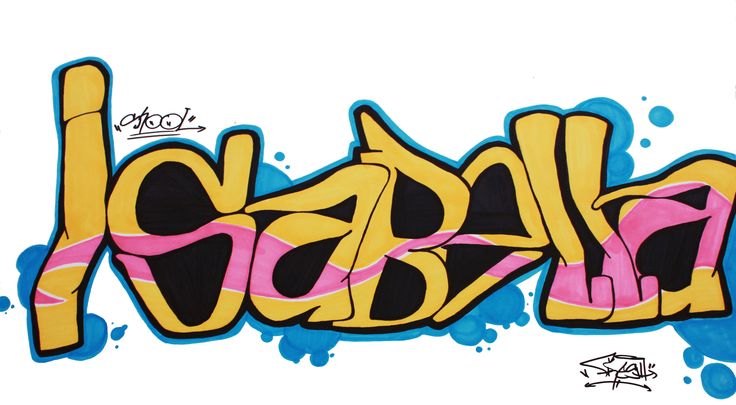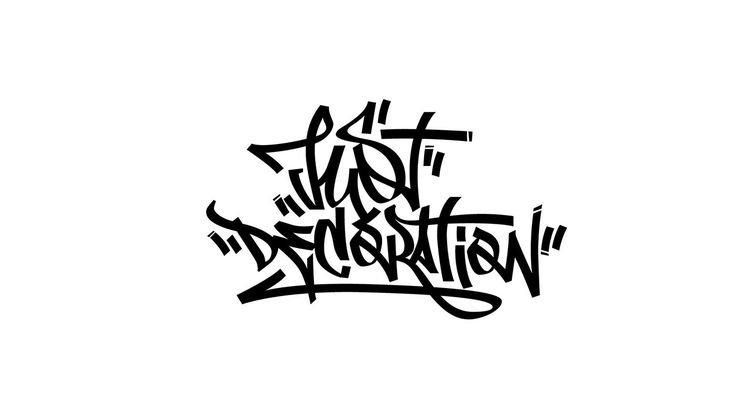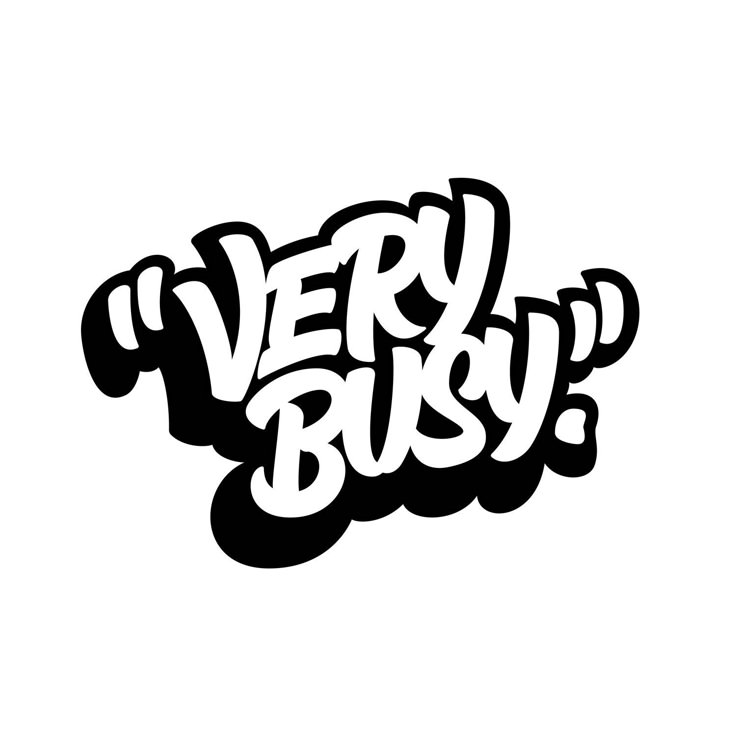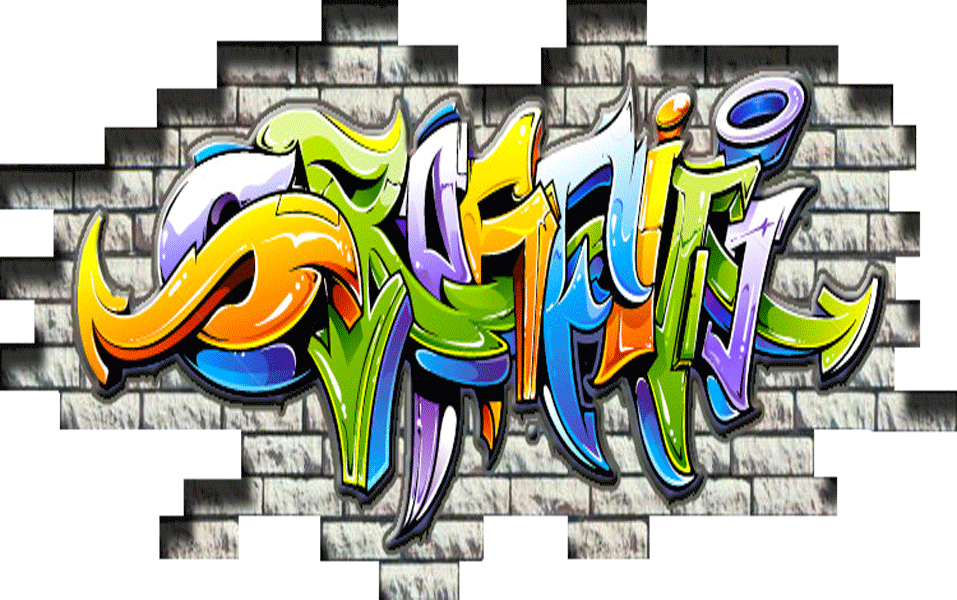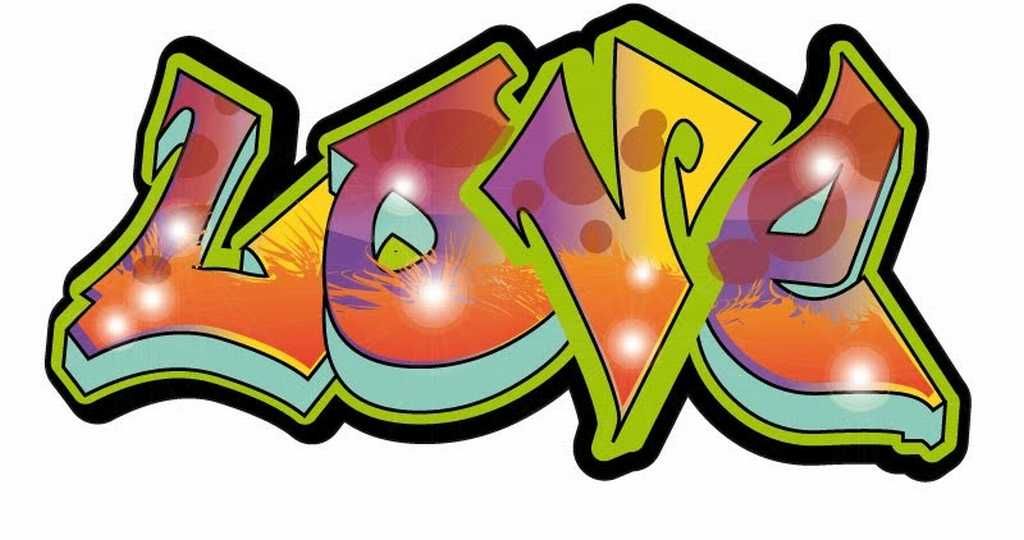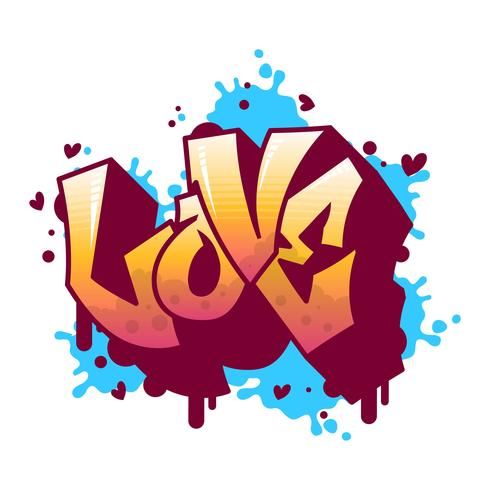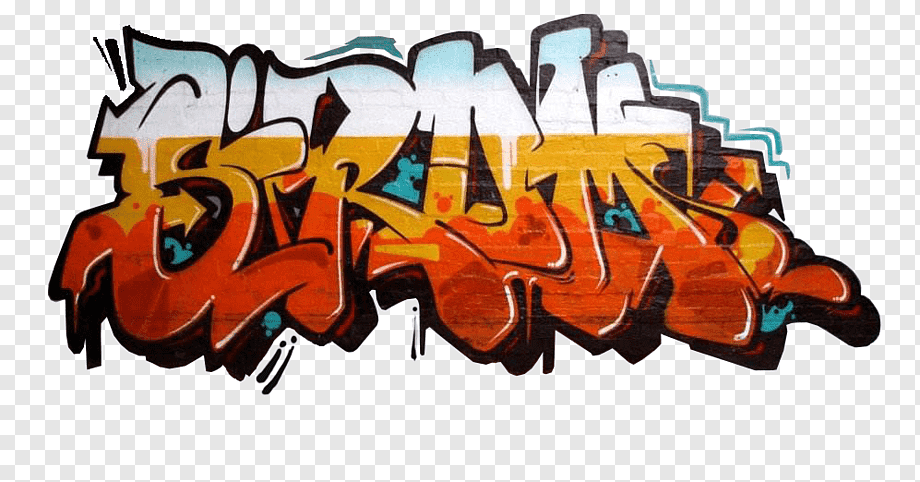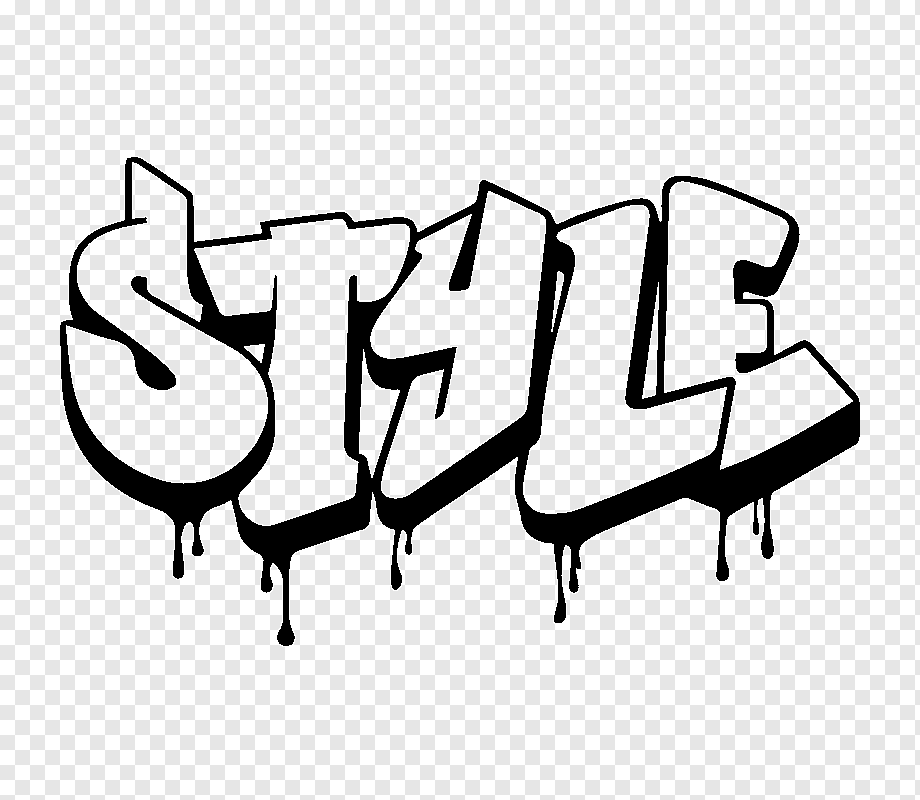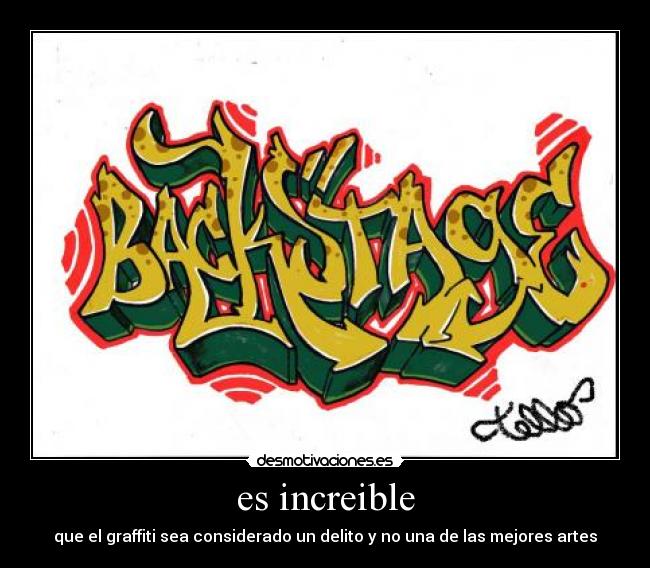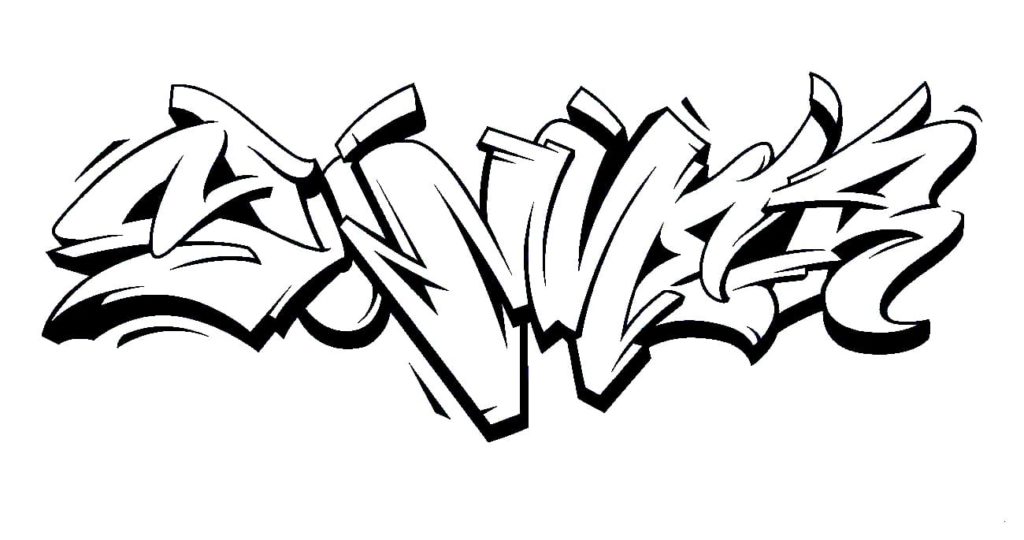
Эффект граффити — Photoshop
Предлагаю Вам один из самых интересных уроков о том, как сделать эффект граффити на стене, используя инструменты Photoshop.
Итак, давайте начнём! Первым делом было бы хорошо найти подходящую текстуру. Я попробовал вот эту. Откроем этот файл и начнём стилизовать текстуру. Для начала используем меню Image > Adjustments > Hue/Saturation со следующими настройками.
Исправим оттенок, насыщенность и яркость для выбранной текстуры. Ваш результат должен быть похож на этот:
Отлично, переходим к следующему шагу. Это текстура должна выглядеть лучше после небольшого добавления резкости. Используем инструмент Sharpen Tool и кисть с мягкими краями и размером 400px.
Выглядит лучше, не так ли? Теперь, начнём создавать граффити. Переходим в Google Images и ищем какое-то подходящее изображение (имейте в виду, что мы должны использовать именно рисунок, не фото).
Вот это подойдёт. Откроем его и скопируем на основной холст с текстурой. Поменяем режим слоя для этой картинки на Multiply.
Вы думаете, что его тоже надо стилизовать. У меня есть интересная идея для Вас по этому поводу. Начнём с выбора инструмента Smudge Tool и использования одной из стандартных кистей Photoshop.
Создаём несколько «растянутых» пятен, как на моей картинке ниже:
После этого возьмите инструмент Sharpen Tool, чтобы сделать их резче.
Этот дизайн выглядит незаконченным без некоторого текста, не правда ли? Возьмём инструмент Horizontal Type Tool и напишем какой-то текст, в этом случае я написал текст в две строчки.
Шрифт под граффити, который я использовал выше, называется Eraser, и Вы можете загрузить его абсолютно бесплатно отсюда. После этого, как Вы закончите с настройками текста, определите его расположение и с помощью меню Edit > Transform > Rotate немного переместите его.![]()
Выглядит неплохо, правда? Отлично, переходим к следующему шагу. Надо создать впечатление, что текст наносили трафаретом. Для этого используем инструмент Polygonal Lasso Tool и создаем выделение, как на моем рисунке ниже.
После этого инвертируйте выделенную область с помощью сочетания Ctrl+Shift+I и возьмите инструмент Brush Tool, выбрав одну из стандартных кистей Photoshop, чтобы создать пятна черного цвета от распылителя.
Результат должен получиться такой:
Снимите выделения с помощью сочетания Ctrl+D. Мы закончили на этот раз! Наслаждайтесь своим собственным прикольным граффити и не бойтесь экспериментов!